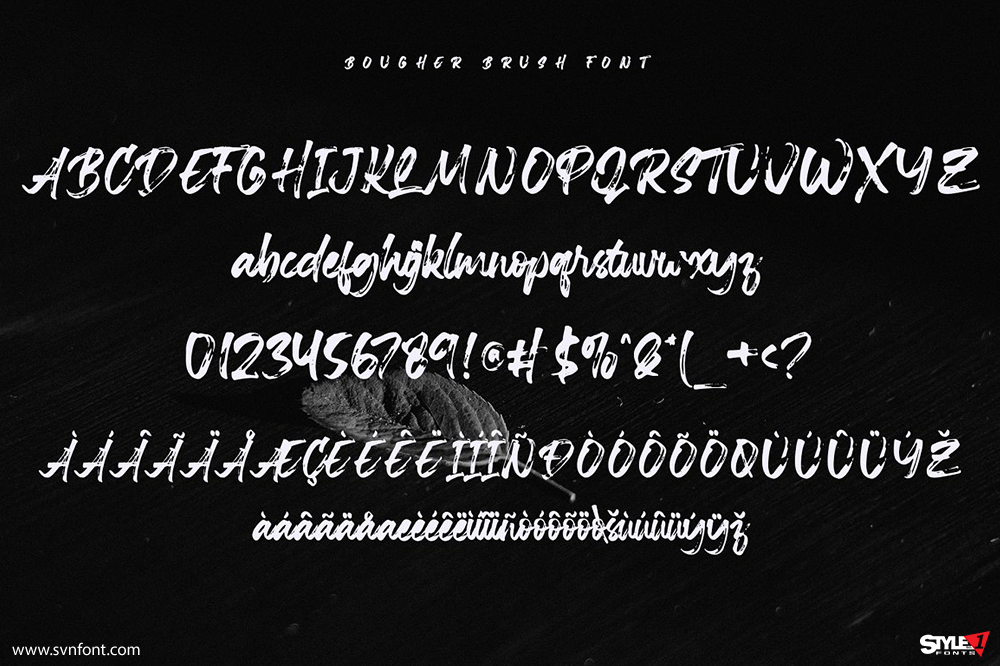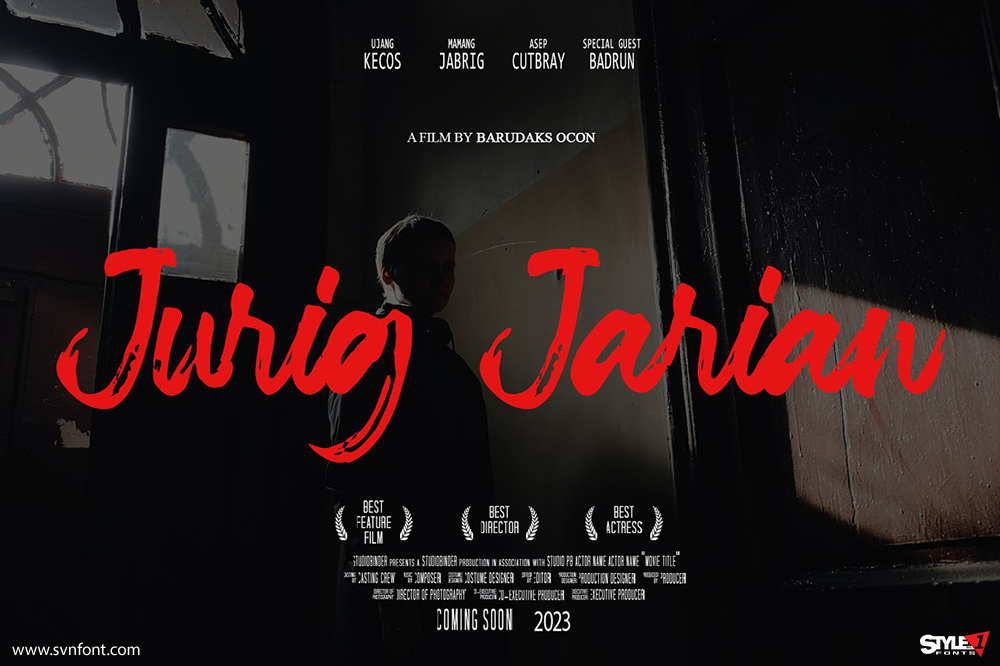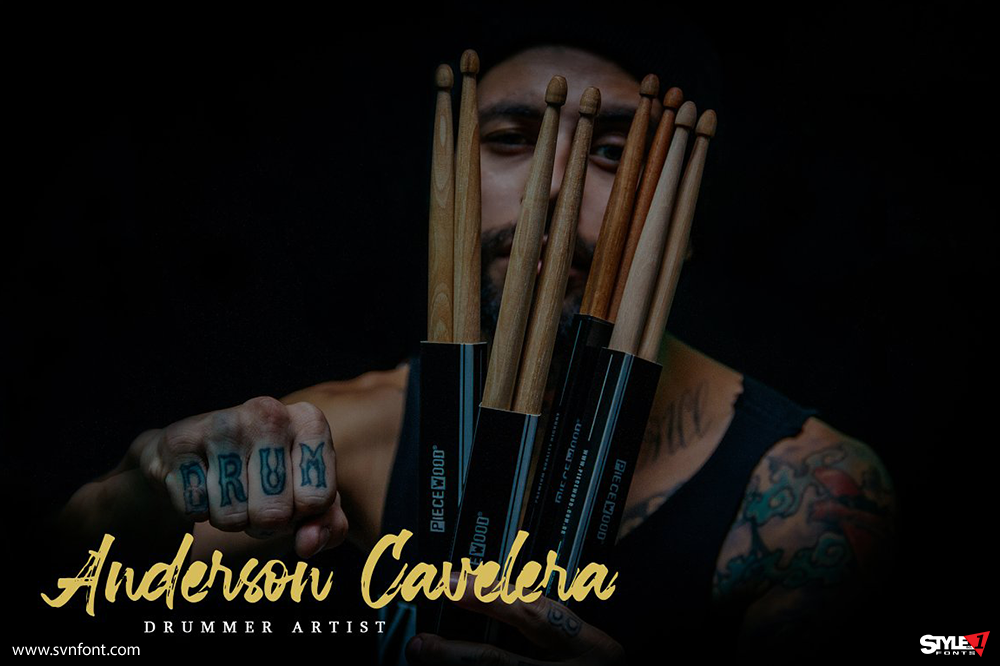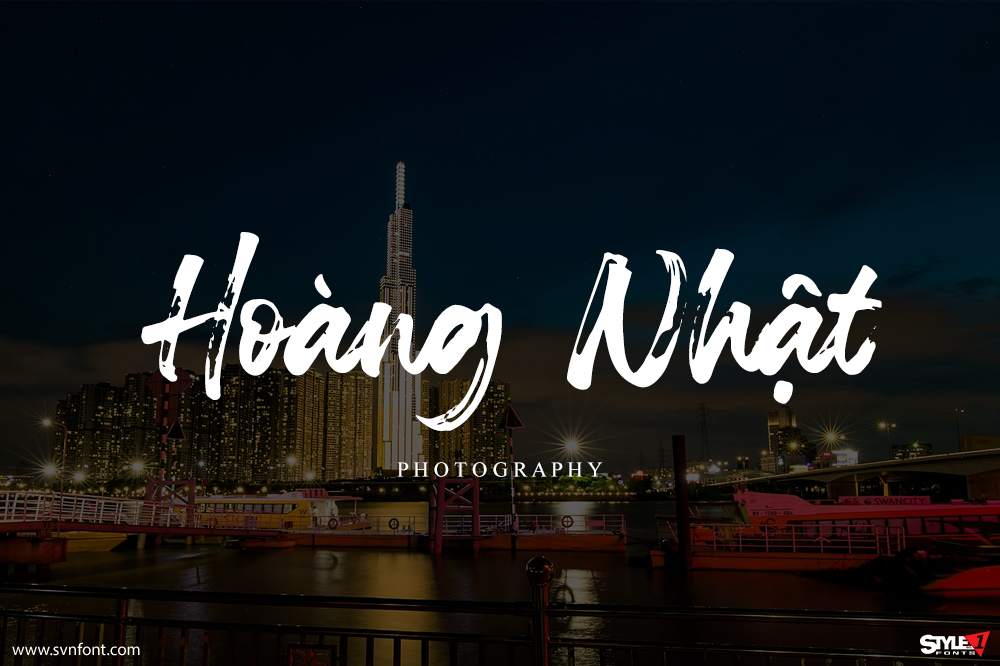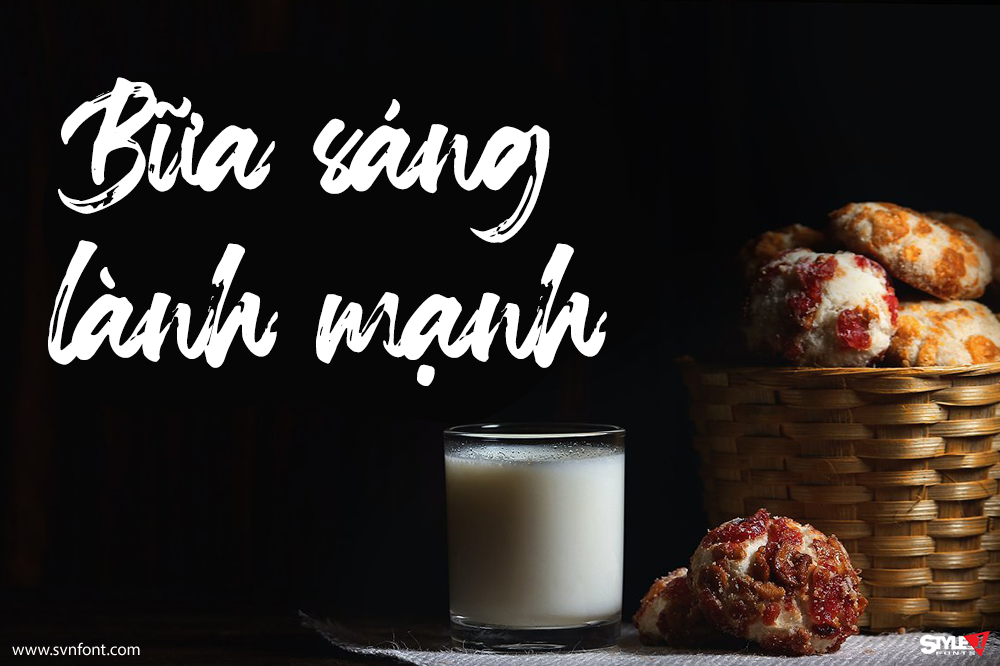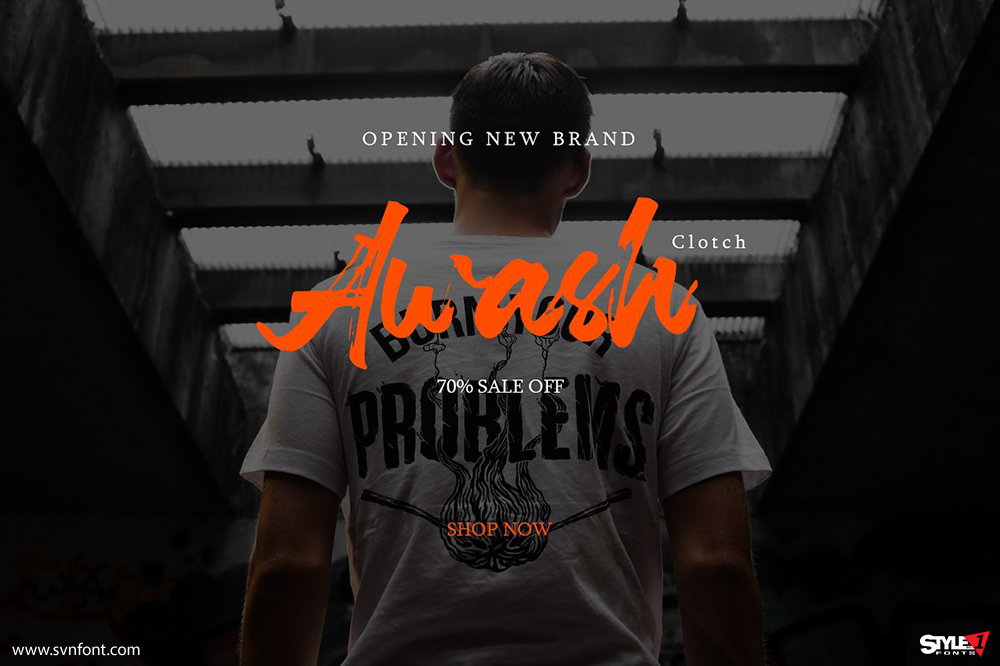
Bougher là một font brush mang phong cách đương đại, được vẽ tay tự nhiên với đường baseline không đều, tạo cảm giác phóng khoáng và giàu cảm xúc. Font đặc biệt phù hợp cho các thiết kế tiêu đề, như thời trang, thiệp mời, bìa sách, văn phòng phẩm, trích dẫn, branding, logo, thiệp chúc mừng, áo thun, bao bì, poster và nhiều ứng dụng sáng tạo khác.
Nhà thiết kế: Randi Ilhamsyah
Nhà phát hành: VZ Type